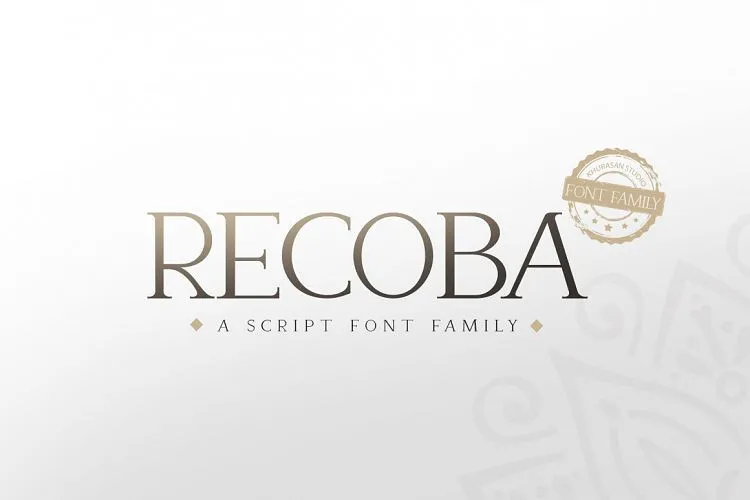
Agradeço a sua atenção para Recoba Typeface. Esta fonte geométrica foi criada com base nas tendências atuais e é perfeita para designs modernos e minimalistas. Ela foi projetada pelo designer khurasan, que compartilhou essa família de fonts elegante e encantadora de serif, tanto moderna quanto lúdica. Recoba oferece três estilos diferentes, fazendo dela uma escolha perfeita para aplicativos variados como posters, logotipos, revistas, capas, banners e t-shirts. Além disso, ela também é adequada para trabalhos de arte em grande escala. Seja você um designer que busca um estilo moderno e sofisticado, ou alguém que quer inovar em uma peça de arte, Recoba está aqui para agradar seus requisitos.